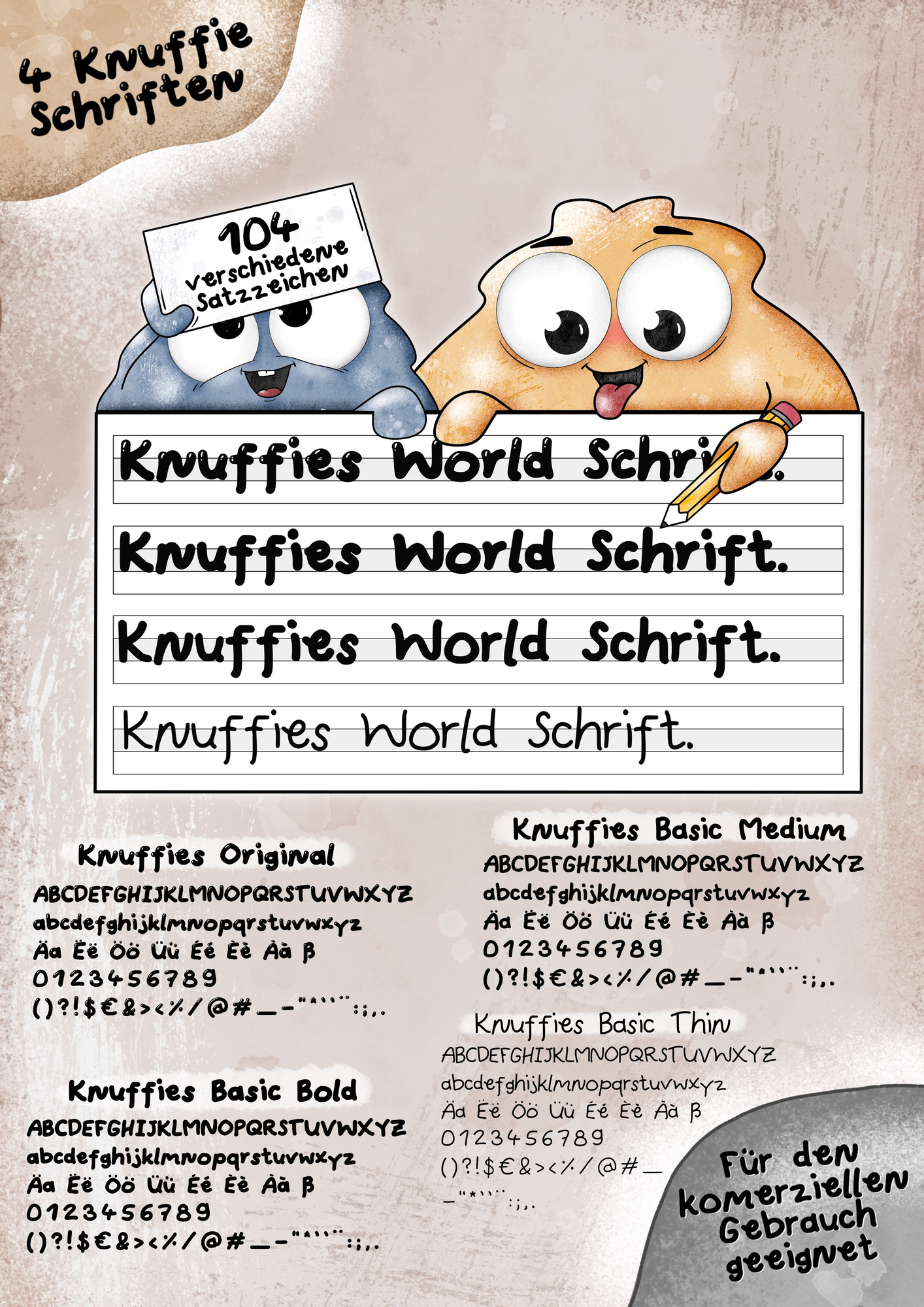
Endlich ist es soweit! Lange habe ich nach geeigneten Schriften für mein Material gesucht und dennoch nie das perfekte gefunden.
Jetzt gibt es endlich meine eigenen knuffigen Schriftarten: die Knuffies Schriften! Eine Sammlung aus 4 selbst erstellen Schriftarten, welche deinem Material einen einzigartigen Touch verleihen.
Jede Schriftart besteht aus 104 verschiedenen Schriftzeichen und ist somit perfekt für jeden Gebrauch und für die komerzielle Nutzung geeignet!